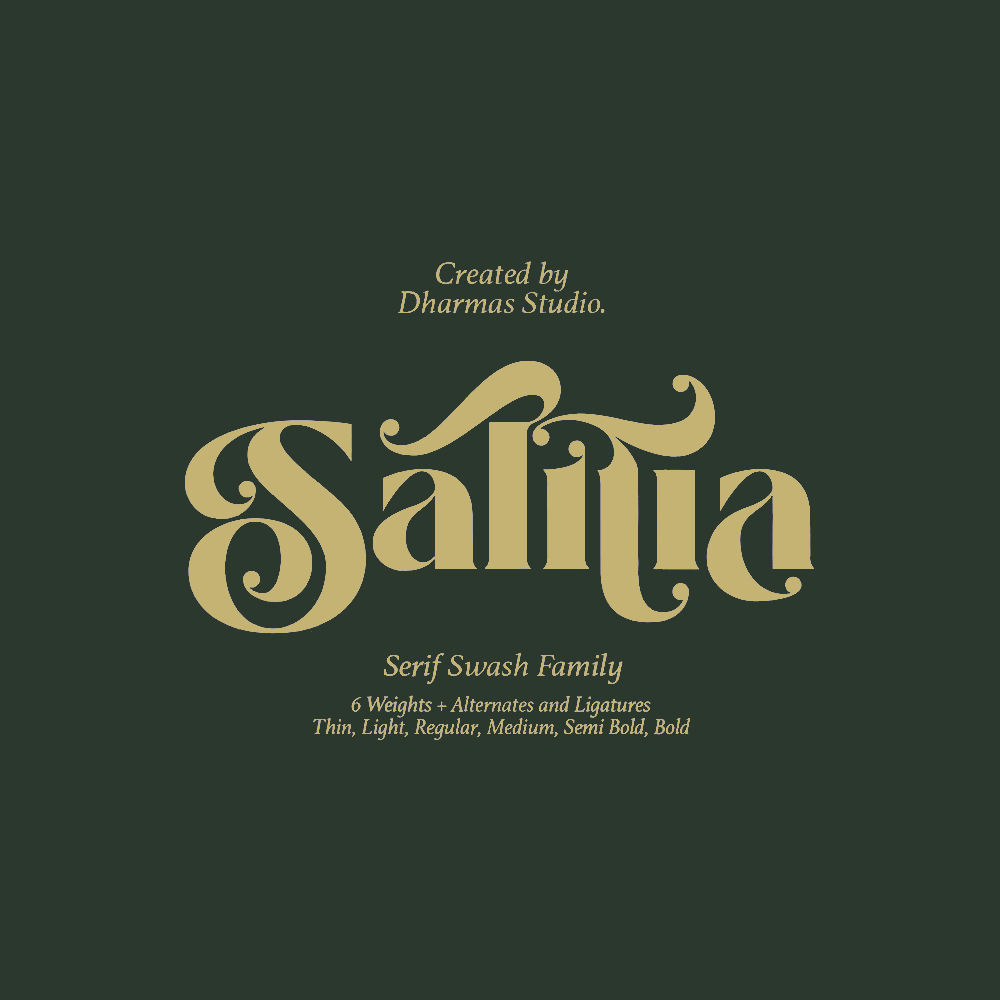
فونت پرمیوم و انگلیسی Salitia یک خانواده مدرن از سریف با فاصله کم است که یادآور دهه‌های ۸۰ و ۹۰ میلادی است. Salitia با ۶ وزن (نازک تا سنگین) و لیگاتورهای منحصر به فرد و جایگزین‌های زیبا برای متن کوتاه و کلمات طولانی مانند تیترها، لوگوها، طراحی رابط کاربری، متن مجله، توضیحات محصول و سایر نیازهای طراحی مناسب است.
مزایای استفاده از فونت لاتین Salitia Font چیست؟
• گلیف های استاندارد
• فونت انگلیسی آنلاین عددی و عملکردی
• فونت انگلیسی برای لوگو جایگزین و لیگاتور